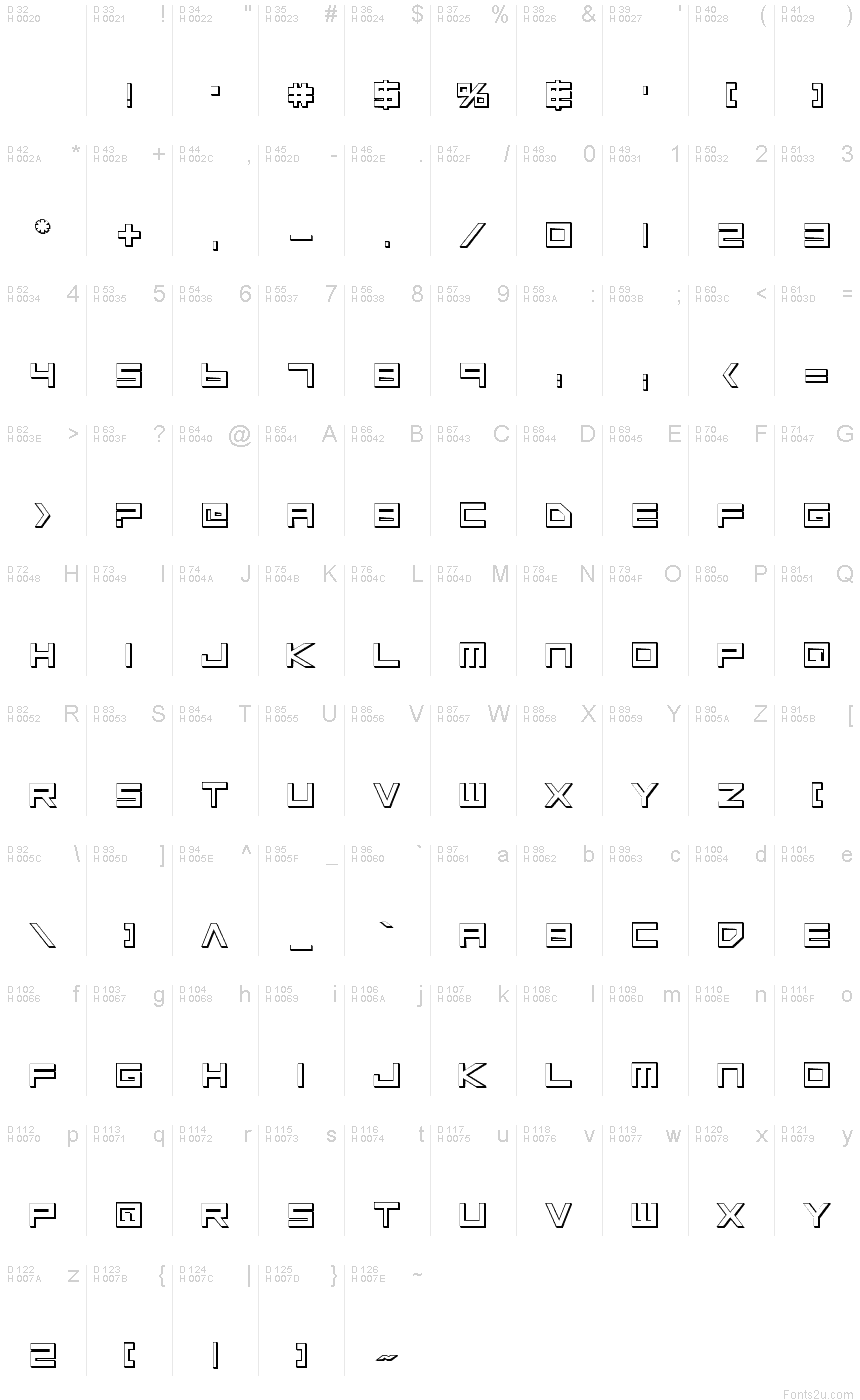
Low Gun Screen Bold 3D, rilasciato da Iconian Fonts nel 2007, è un font 3D techno gratuito a caratteri maiuscoli, costruito con contorni quadrati e cornici incassate. Le lettere appaiono ampie, rigide e simili a un'interfaccia a schermo, con bordi stratificati che suggeriscono profondità senza ricorrere a curve o ornamenti.
Questo font gratuito è ideale per titoli arcade, poster di fantascienza, loghi esport, copertine di album elettronici, confezioni di giochi e schede titoli animate. La sua struttura squadrata è perfetta per titoli brevi e marchi compatti, dove i contorni interni ripetuti creano un solido impatto digitale.